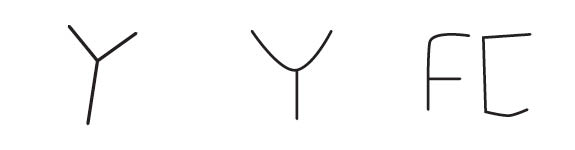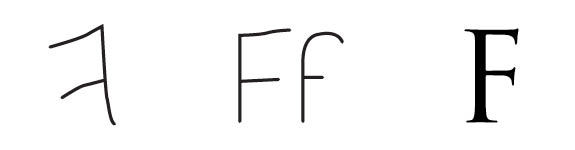
| Jeroglífico 3000 aC • Fenicio 1100 aC • Griego occidental 400 aC |
| Etrusco 800 aC • Latin clásico 200 aC • Romano 100 aC |
Séptima letra del abecedario español y sexta del orden latino internacional. Su nombre es efe.
Su forma deriva de la letra fenicia waw, que poseía el valor fonético [w]. De ésta derivó la digamma griega, que luego desapareció. Los etruscos tomaron la letra digamma aunque mutaron su valor fonético por el de [f] y con éste llegó al alfabeto latino.
La minúscula es una estilización de la mayúscula, mas alargada en sus diseños antiguos, y se usó con frecuencia como “s” minúscula.
Tipografía Munro, estudiante Melania Lozano T3. 2014
Antonio Basoli. De su serie de litografÌas "Alfabeto pictórico" (Italia, 1839)
Ilustración de Federico Galvani (Happycentro, Italia, 2016)
Logotipo de Fender. Jim Cruickshank, 1950.
Trabajo de estudiante, T1 UBA 2016.
Estudiante Lucila Solier-Feiguin, T2 UNL 2015.
Futura es una tipografía sans serif geométrica, diseñada por Paul Renner en 1927.
F realizada en cerámica por Ariel Marciano.